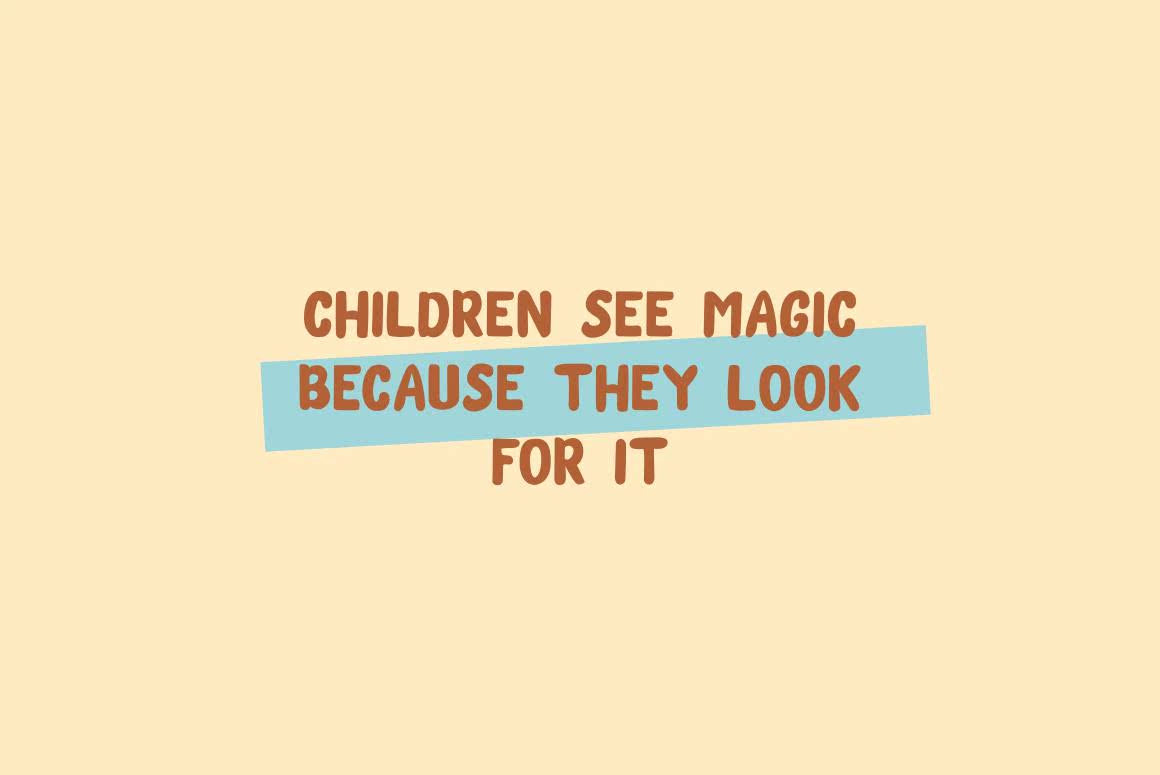
ChocoBubble是一种有趣且古怪的显示字体。ItemBody可显示字体的完整性和身份验证,并可区分所有儿童活动或学校项目的完美选择。将此Chunkylettered字体添加到您的设计中,并注意它如何使您的手机充满活力!ChocoBubble是一种有趣且古怪的显示字体。ItemBody可显示字体的完整性和身份验证,并可区分所有儿童活动或学校项目的完美选择。将此Chunkylettered字体添加到您的设计中,并注意它如何使您的手机充满活力!